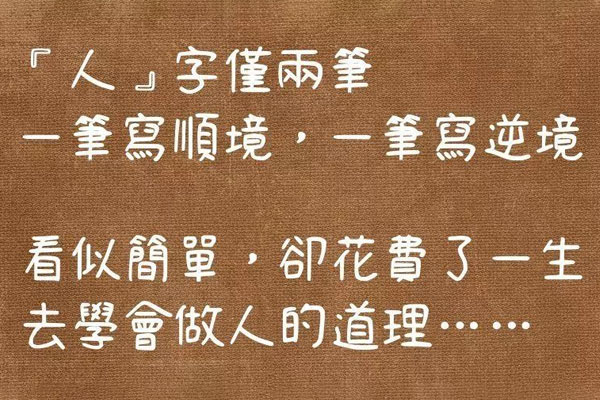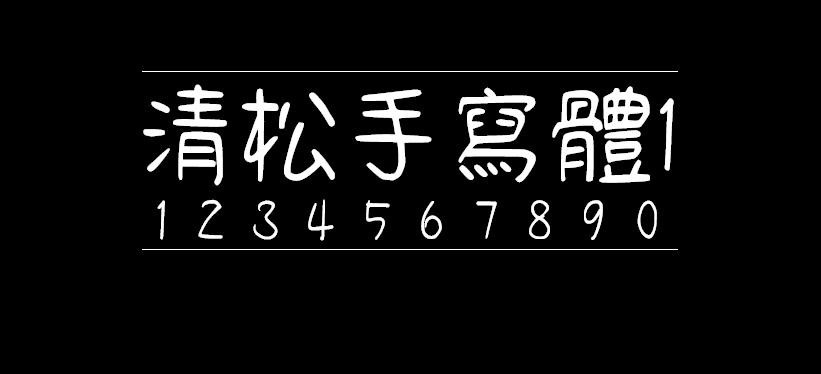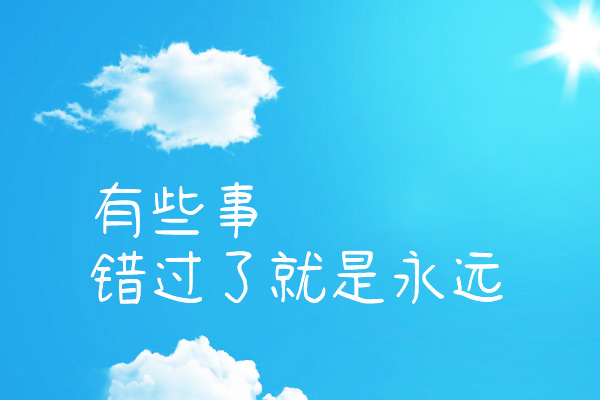
清松手写体1
清松手写体,是一款来自台湾的字体,它由游清松建立,游清松曾在飞信半导体担任工程师,颀邦科技担任资深工程师,敏杰科技股份有限公司担任工程师。为了创建这个字体,他还成立了一个小组: 「顺其字然」,首先在稿纸上用原子笔手写,产生初稿字体,再经过软件加工的为电脑可用字体。清松手写体按照计划会有多个不同的字形版本,当前这个是“清松手写体1”也就是第一个版本。 清松手写体没有一般计算机字型的生硬感,多了几分手写般的自然感。不论是中文、英文、符号数字,适合在计算机屏幕上阅读、排版,打印出来效果也很棒的! 开放给所有人(包含商用)免费使用,目前已经收录超过 8000 个字(支持简体和繁体)。